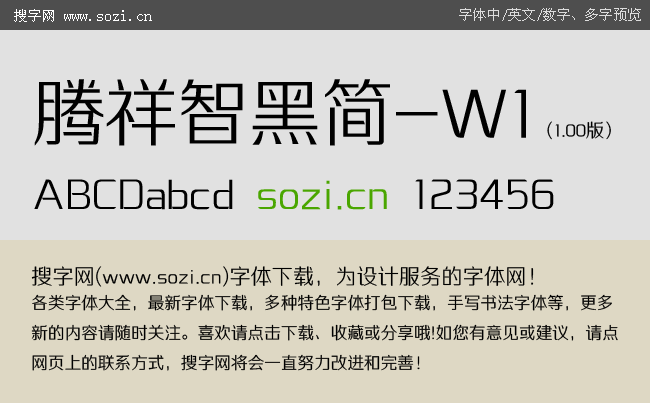
騰祥智黑簡(jiǎn)-W1
搜字網(wǎng)提供一款非常藝術(shù)的黑體字騰祥智黑簡(jiǎn)-W1下載,騰祥智黑是騰祥睿黑的姊妹篇,風(fēng)格相近但排版效果迥異,騰祥智黑與騰祥睿黑的差別在于更加強(qiáng)調(diào)了黑體的特征,筆畫(huà)簡(jiǎn)潔、硬朗更穩(wěn)重大方;字形結(jié)構(gòu)方正、端莊,橫豎筆畫(huà)挺拔,軟筆畫(huà)細(xì)膩、柔美。點(diǎn)形到撇、捺形都做了大膽的創(chuàng)新,塔形頓點(diǎn)、撇點(diǎn)賦予了智黑特殊的設(shè)計(jì)效果,富于設(shè)計(jì)感,適用于包裝印刷、廣告設(shè)計(jì)、平面設(shè)計(jì)、書(shū)籍報(bào)紙等領(lǐng)域。